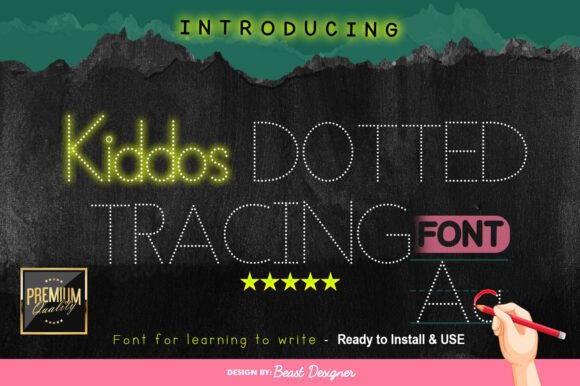
Kiddos Learning Dotted
Doğru tasarım öğelerini bulmak zor olabilir, ancak Kiddos Learning Dotted, çalışmanızı anında bir üst seviyeye taşıyan olağanüstü bir koleksiyon sunar.
İster İsteğe Bağlı Baskı (POD) ürünleri, ister düğün davetiyeleri veya sosyal medya grafikleri oluşturuyor olun, Kiddos Learning Dotted ideal bir uyumdur.